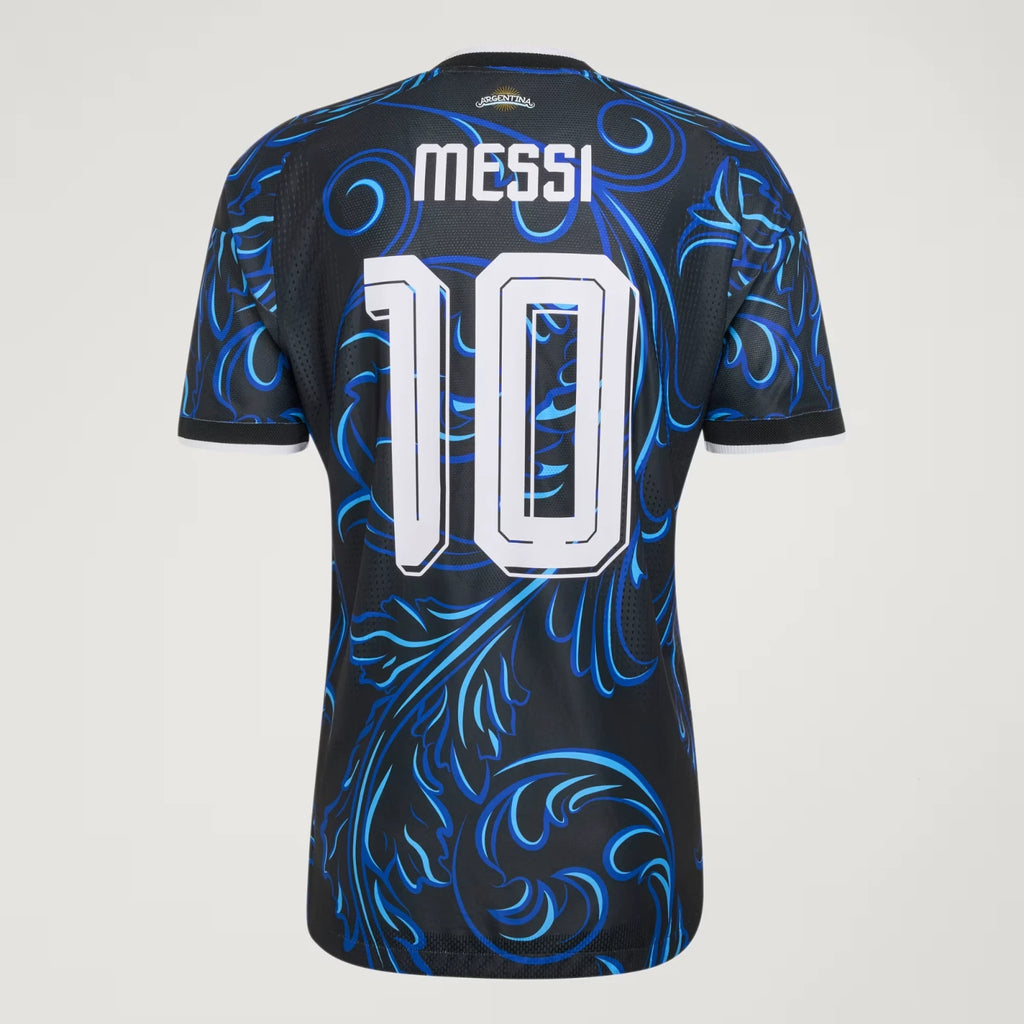
TIPOGRAFIA SELECCION ARGENTINA VISITANTE MUNDIAL 2026
TIPOGRAFIA PARA UNIFORME DE ARGENTINA VISITANTE MUNDIAL 2026 SIN LOGO VECTORIZADA IDEAL PARA ESTAMPAR UNIFORMES Y REALIZAR DISEÑOS
TIPOGRAFIA PARA TODAS LAS SELECCIONES QUE VISTE LA MARCA